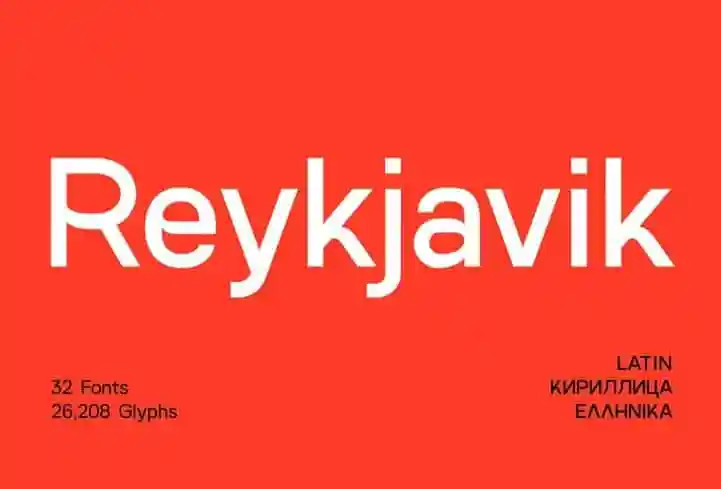
SK Reykjavik Sans Serif Font – Download Grátis
A SK Reykjavik Sans Serif Font é uma tipografia versátil inspirada nas vibrações dinâmicas do movimento global. Composta por dois pesos que se complementam perfeitamente, esta fonte apresenta um design geométrico moderno e elegante, com caracteres sans-serif e serif. Inspirado pelo designer Salih Kizilkaya através da plataforma de criação 99designs, ela destaca-se por seu impacto visual máximo, oferecendo uma completa cobertura para a tipografia em alfabetos latino, grego, cirílico e báltico. Além disso, SK Reykjavik Sans Serif Font é extremamente versátil, com 32 fontes disponíveis. Este conjunto de recursos inclui um total de 26,208 guionizadores, garantindo uma experiência impecável para designers, gráficos e tipógrafos. A presença destas figuras em múltiplos idiomas e suas possíveis combinações o tornam uma fonte indispensável para projetos que exigem uma linguagem visual inovadora, de estampas até elementos em negrito, sem esquecer de qualquer detalhe importante.